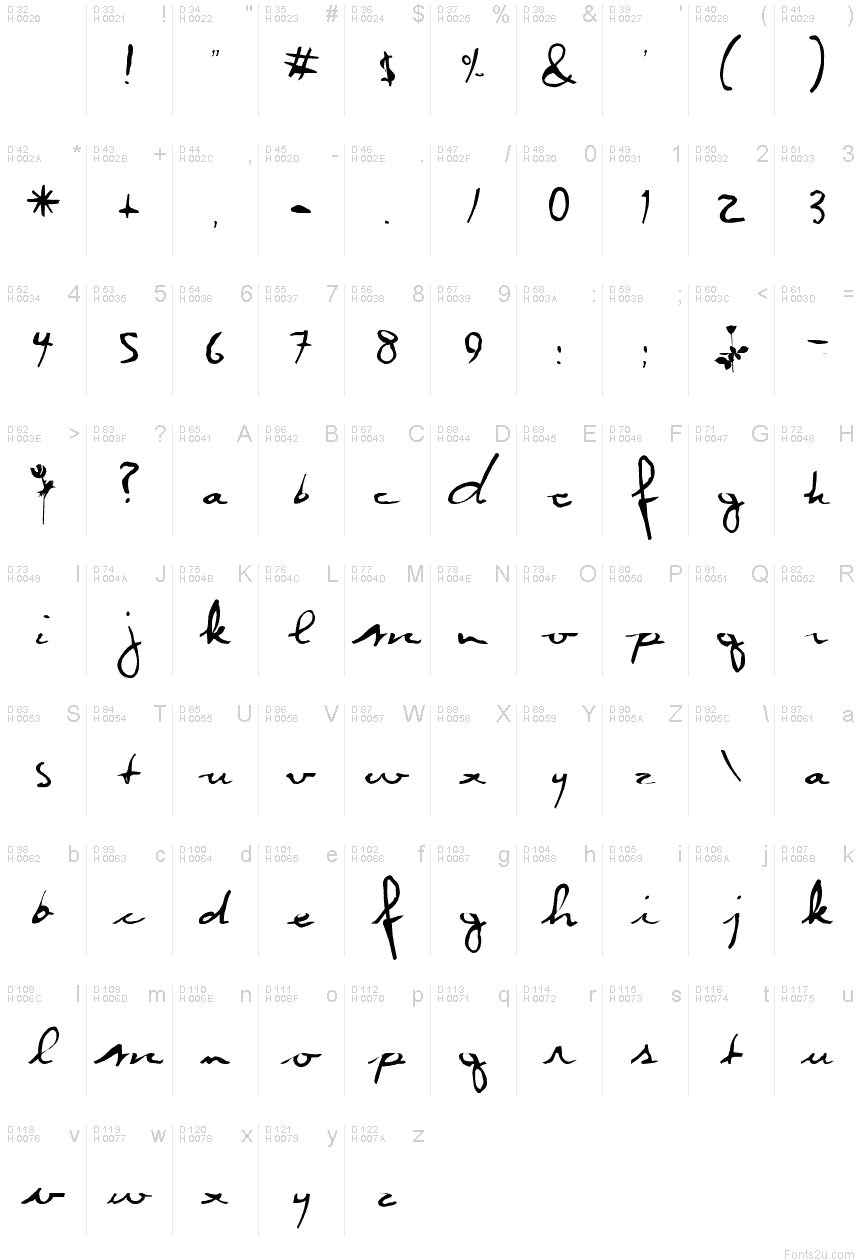
Violation هو خط يدوي مجاني يتميز بإيقاع حر ومائل وطابع متمرد بلمسة فرشاة. تتصل الحروف ببعضها في خط انسيابي، لكن تغير سمك الخط والتفاصيل الحادة تمنحه لمسة عفوية بعيدة كل البعد عن التكلف أو التنميق.
إنه مثالي لعناوين الملصقات، والنشرات الموسيقية، وأغلفة المجلات، واسكتشات الشعارات، والعناوين التحريرية السريعة، حيث يمكن لخط مجاني يتمتع بهذا القدر من الحيوية أن يغني عن استخدام الصور. استخدمه للكلمات القصيرة، أو نصوص الأغلفة، أو شعار مميز بأسلوب التوقيع، خاصة عندما تريد أن تبدو الكتابة عفوية وغير رسمية.